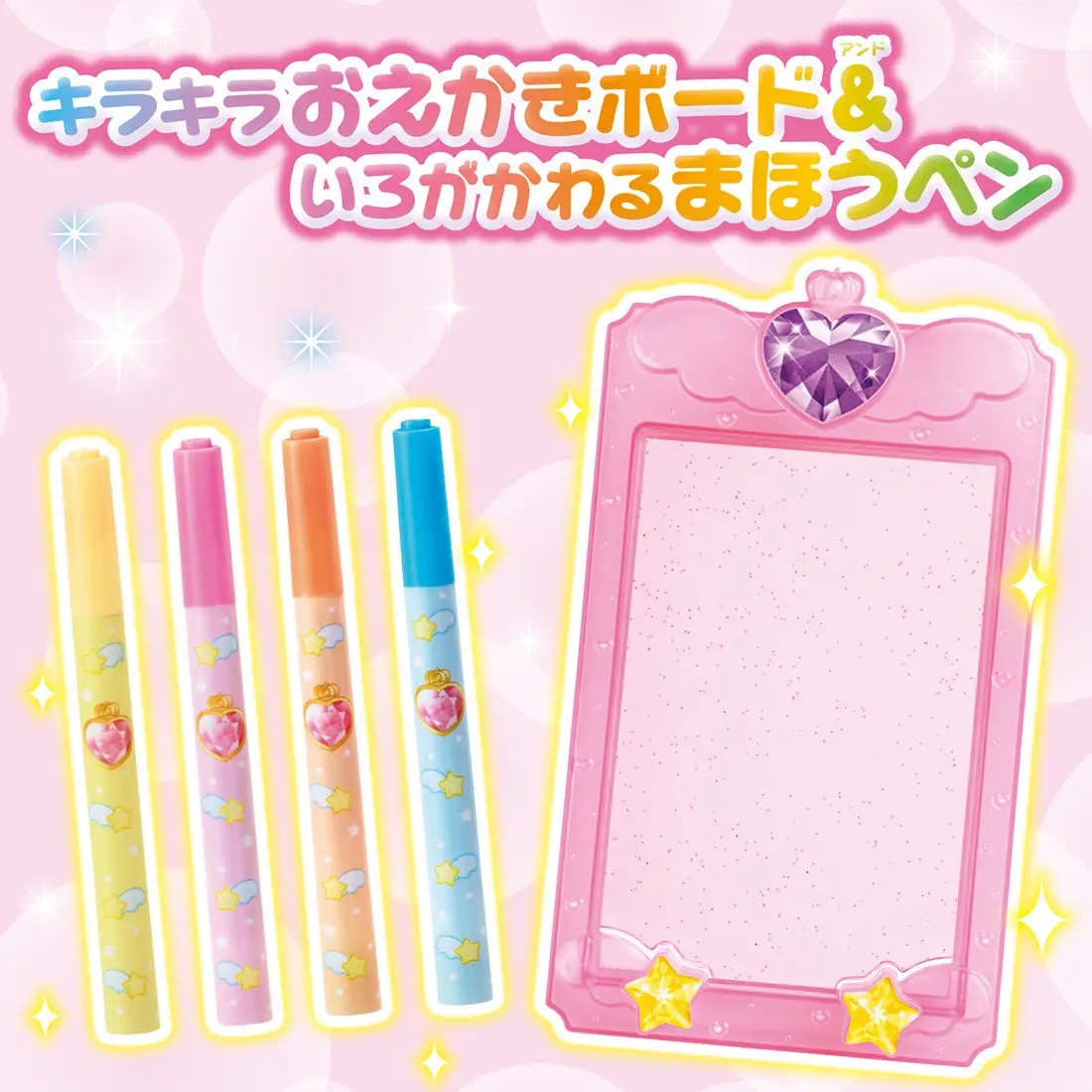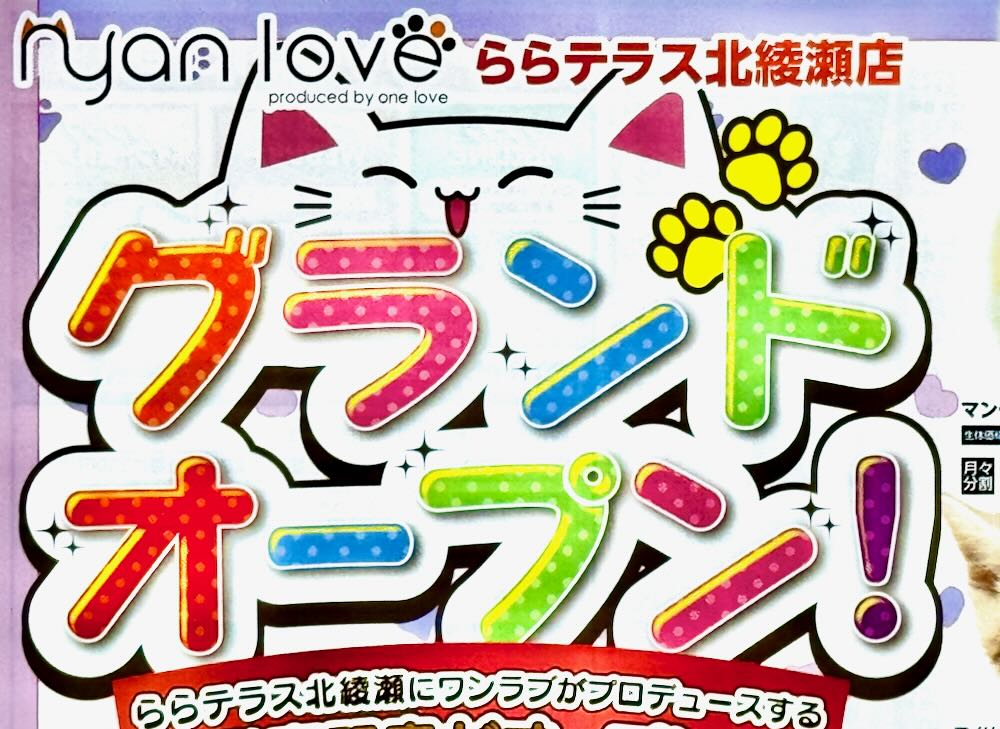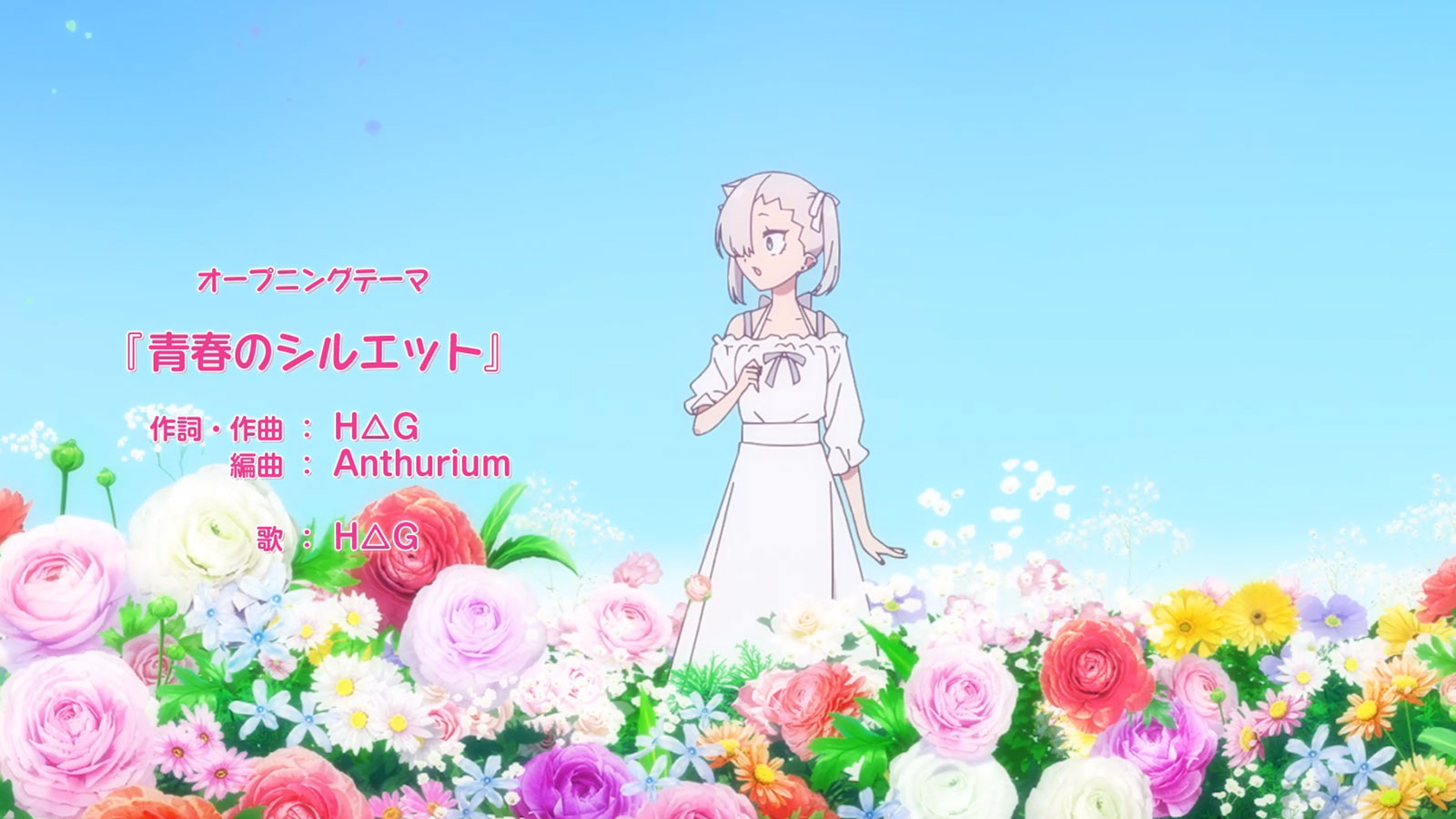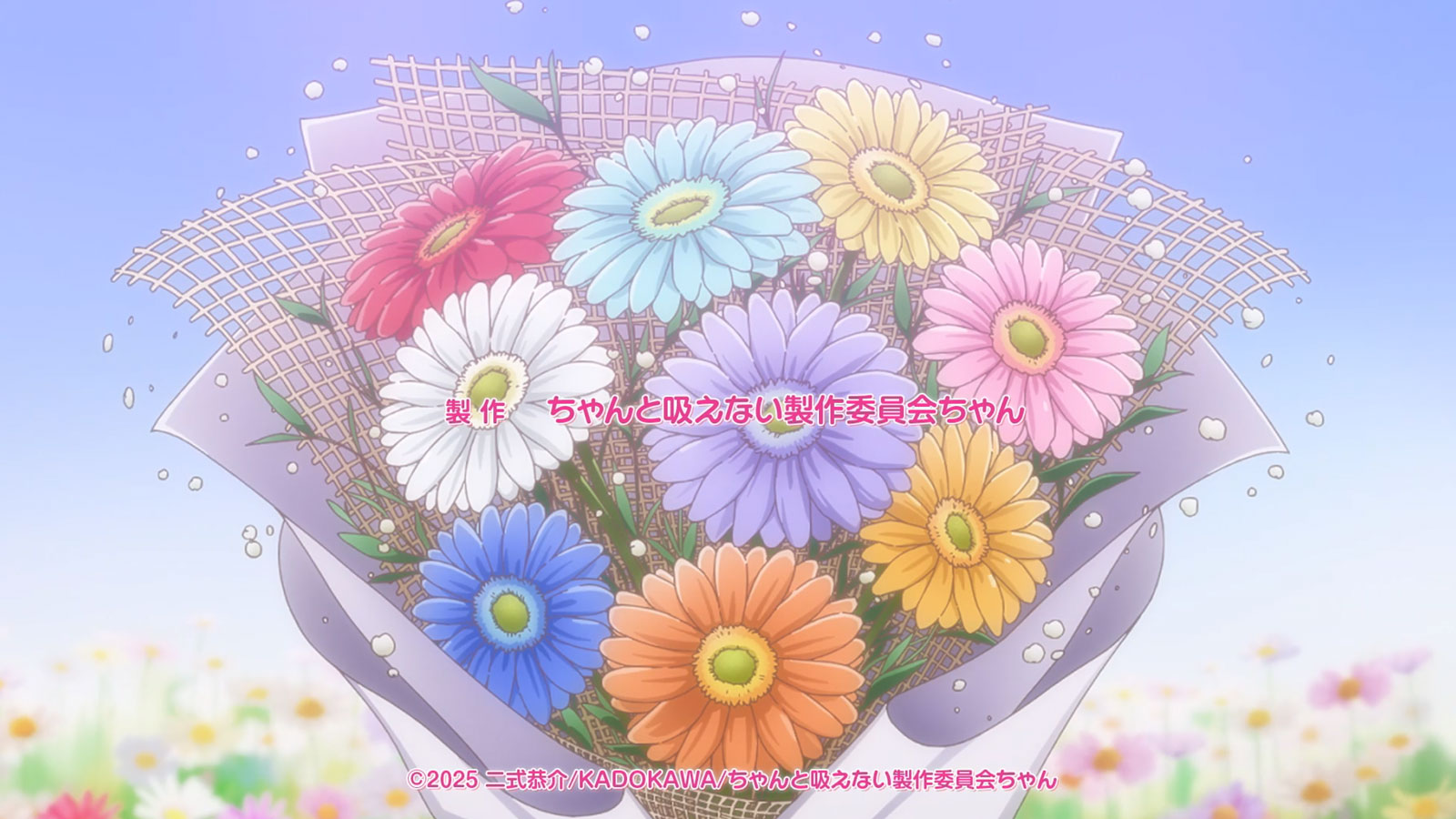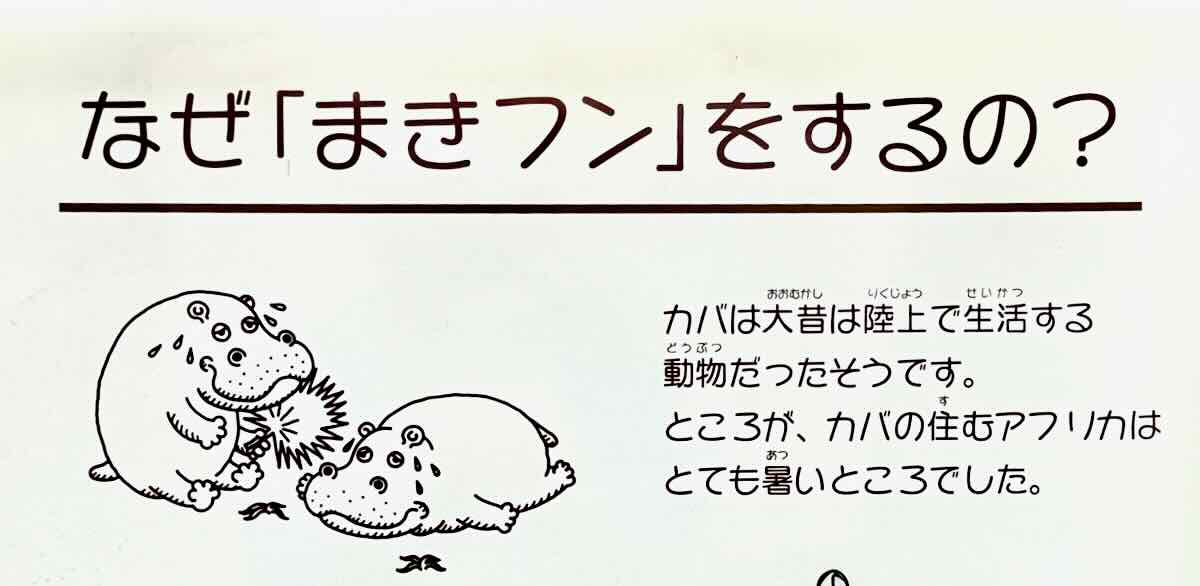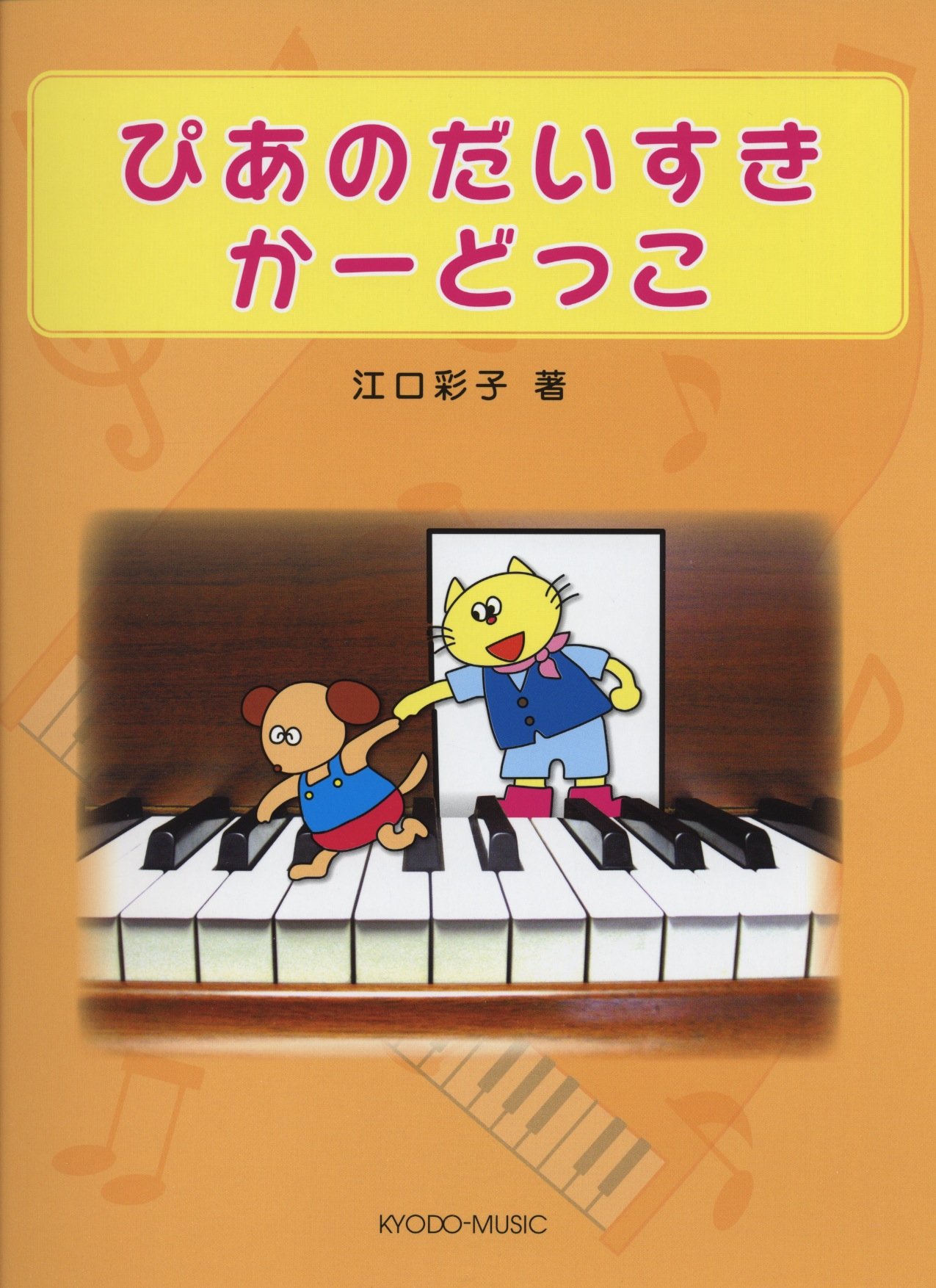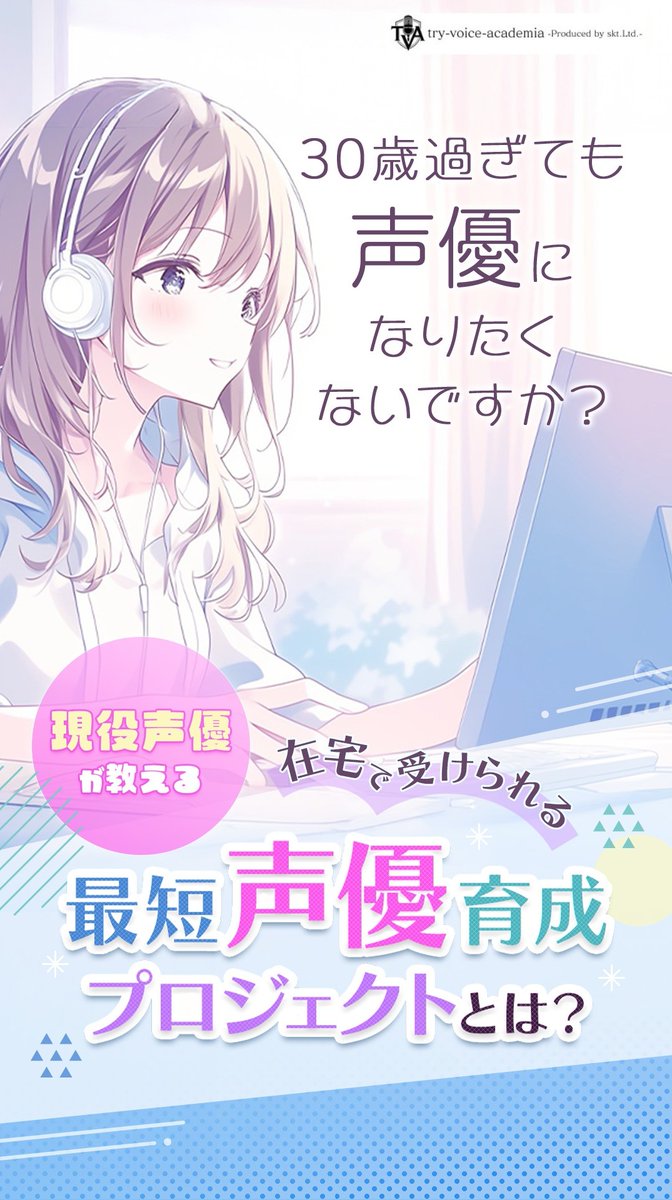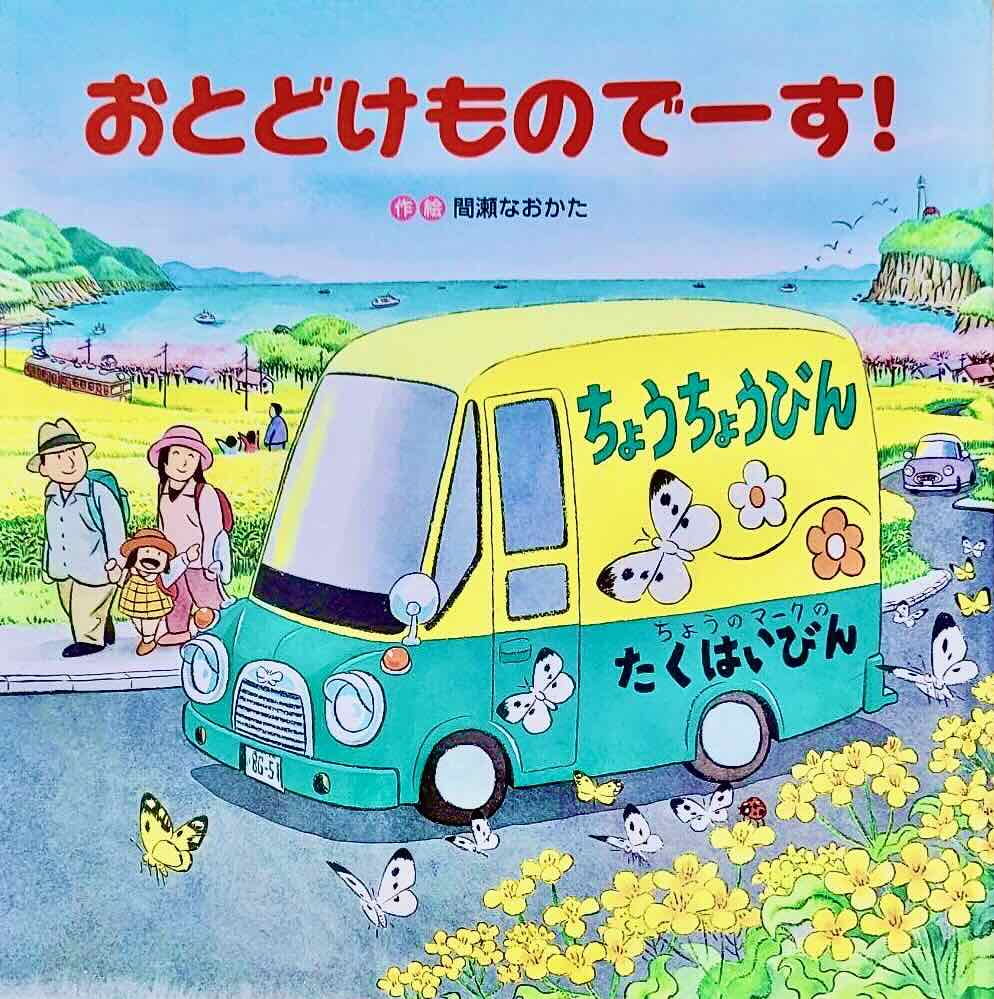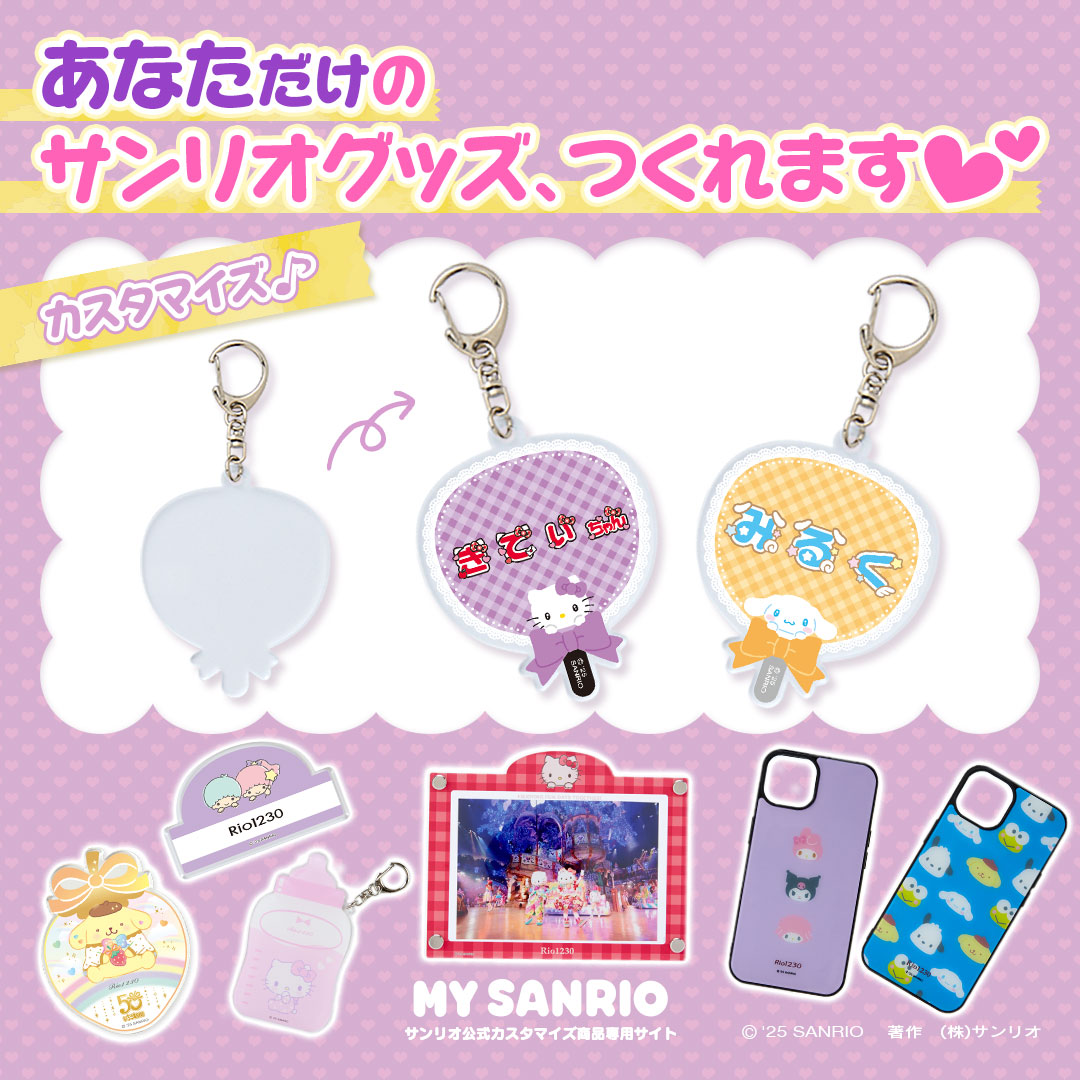
タイプラボが頒布している「キャパニト」「キャピレラ」だけでなく
かな書体「キャピー」は、フォントワークスやモリサワからも販売されています
本の表紙 さとうゆたか
書名:ケアの“超レベル上げ”講座
著者:杉本浩司(著)、佐々木淳(監修)
発行:中央法規出版
さとうゆたか
これも…。
本の表紙 さとうゆたか
書名:おとどけものでーす!
著者:間瀬直方
発行:ひさかたチャイルド
本の表紙 さとうゆたか
書名:どうぶつなかよし
やなせたかし/原作
トムス・エンタテインメント/作画
発行:フレーベル館
Xの広告 takumi
Xで見つけた広告。
「30歳過ぎても〜」は、たぶんキャピレラですね。
さとうゆたか
数字のデザインを見る限り、たしかにキャピレラですね〜。
本の表紙 さとうゆたか
書名:ぴあのだいすきかーどっこ [ 江口彩子 ]
著者:江口彩子
発行:共同音楽出版社
カバの説明 さとうゆたか
先日いった大阪の天王寺動物園で見つけた。
あ さとうゆたか
全体表示。
イベントポスター さとうゆたか
東武博物館 冬休みイベントについて
本の表紙 さとうゆたか
書名:ふしぎなおばあちゃん×12
著者:柏葉 幸子 絵:もりちか
発行:講談社
広告画像 さとうゆたか
「MY SANRIO」
アニメのオープニング takumi
放送中のアニメ「ちゃんと吸えない吸血鬼ちゃん」のオープニングより。
国内M社の、総合書体化された「キャピー」フォントが使われていました。
takumi
もう1枚。
さとうゆたか
小さく上品に使われていますね。